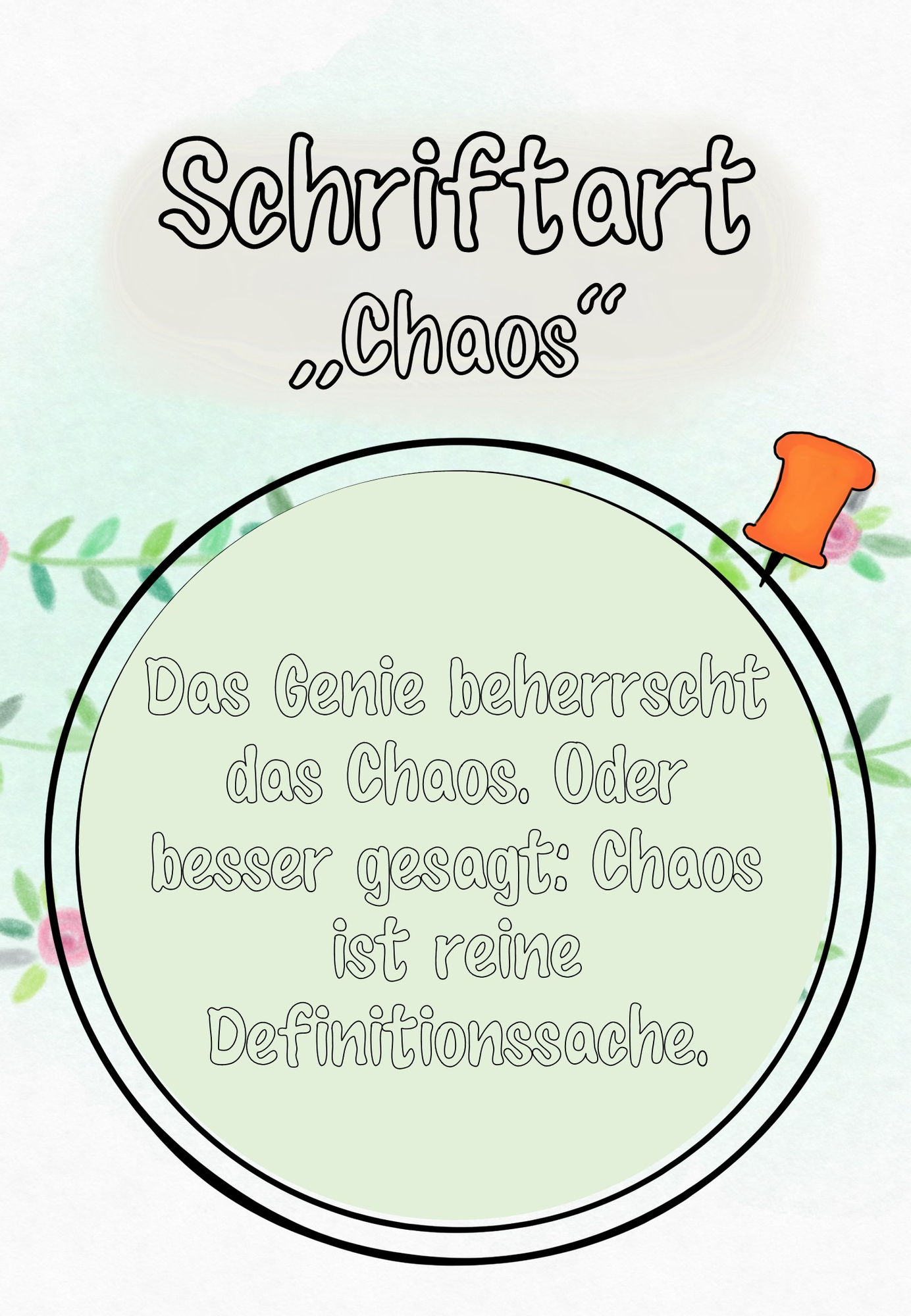
selbst erstellte Schriftarten - Schriftart "Chaos" - grundschulliebe_s - Deckblatt
Eine Hohlschrift, besonders geeignet für Überschriften.
Schriftart "Chaos"